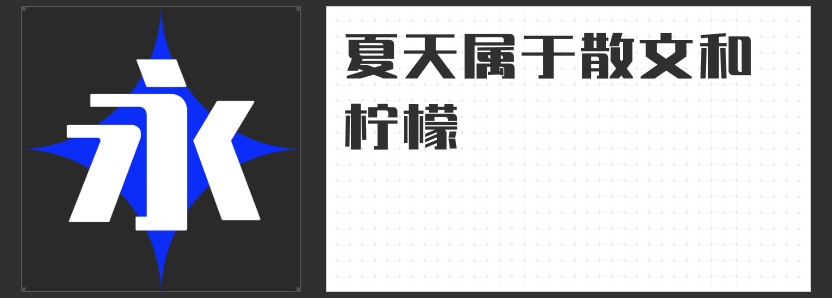
电商设计新宠:四款精选字体推荐
在电商设计中,字体不仅是传递信息的工具,更是塑造品牌形象和营造购物氛围的关键元素。今天,为大家推荐四款特别适合电商使用的字体,它们各具特色,能够满足不同场景下的设计需求。
一、造字侠今朝醉简:白酒包装的首选
造字侠今朝醉简是一款毛笔楷书字体,其收笔潇洒凌厉,如同醉酒一般自由不羁。笔法正统酣畅,劲健雄浑,展现出浓厚的文化底蕴和艺术气息。这款字体特别适用于白酒包装等场景,能够完美诠释中国传统酒文化的精髓,让产品更具吸引力和辨识度。
二、励字志向黑简 中粗:屏显时代的稳重之选
励字志向黑简 中粗巧妙地将圆体与黑体融合,通过增加笔画拐角的外圆角,为整体稳重大气的字形增添了一丝灵动。这款字体字面充实,结构稳定,非常适合屏显使用。无论是电商平台的商品标题还是详情页描述,励字志向黑简 中粗都能展现出其独特的魅力,让信息传达更加清晰、有力。
三、励字光芒简 超黑:视觉冲击力爆棚
励字光芒简 超黑是一款以黑体为原型打造的简体字体,笔画粗壮,线条分明。这款字体在文字中的应用极具视觉冲击力,能够迅速吸引消费者的注意力。无论是广告设计、平面设计还是产品包装、报刊杂志等领域,励字光芒简 超黑都能展现出其强大的表现力和感染力。
四、励字大标宋简繁:端庄与力量的完美结合
励字大标宋简繁笔画有粗细变化,横细竖粗,末端装饰部分精致美观。点、撇、捺、钩等笔画尖端锐利,横轻竖重,字形端正、刚劲有力。这款字体结合了老宋体和黑体的特点,既端庄清秀又不失力量感。在电商设计中,励字大标宋简繁能够很好地提升整体设计的品质感和专业性。
综上所述,这四款字体各具特色,能够满足电商设计中的不同需求。选择适合的字体,不仅能够提升信息传达的效率,还能为品牌形象注入更多的文化内涵和艺术价值。